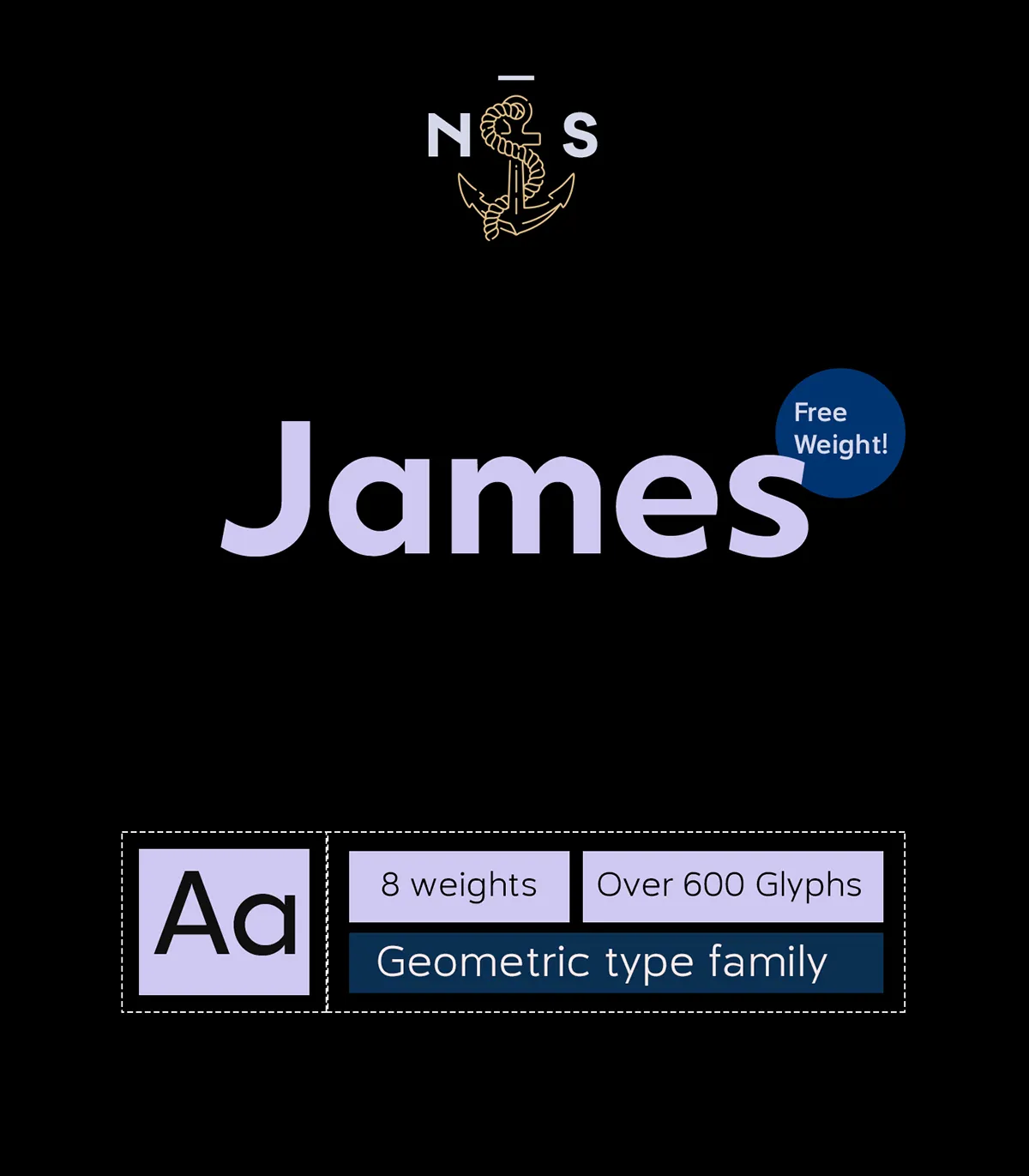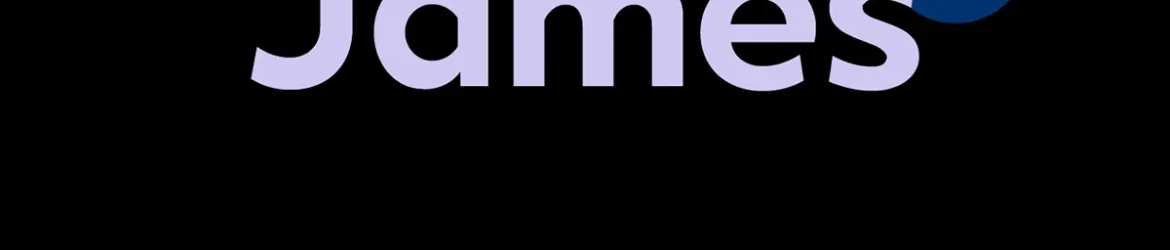
A NS-James Font Family é uma fonte geometrica desenvolvida pela Nautica Studios por Aritra Das. Com 8 pesos, desde “extralight” até “black”, esta família de tipos é perfeita para aplicativos diversos, desde editoriais até websites. O seu recurso único são as altas dimensões x-height, o que torna a legibilidade ótima mesmo em tamanhos pequenos. Ela ainda oferece uma ampla gama de recursos de tipo Open Type. Esta fonte é um marco na produção da Nautica Studios e tem seu preço acessível, fazendo-a altamente adaptável para diferentes ambientes gráficos. Ideal tanto para projetos digitais quanto impressos, NS-James é uma escolha inteligente para designers em busca de uma fonte clara e funcional.